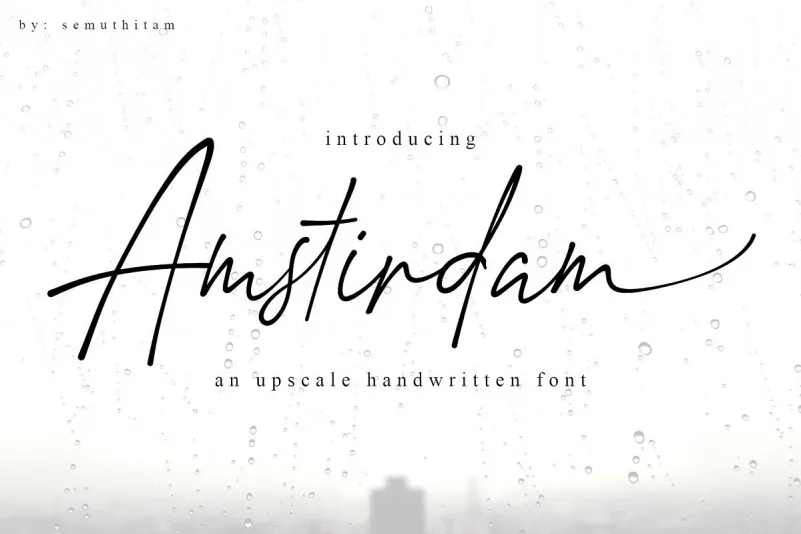
Amstirdam Handwritten Script Font – Download Grátis
Estou aqui uma descrição para a página de download da fonte ‘Amstirdam Handwritten Script Font’, adequada ao estilo e requisitos especificados: Agradecemos por verificar a fonte Amstirdam Font, um belo traço de escrita à mão! Esta tipografia contém inúmeras ligaturas divertidas que conferem ao seu design o toque único e autêntico. É uma tipografia de escrita à mão sofisticada, perfeitamente adequada para diversas finalidades: branding, convites de casamento, cartões de visita, e outros trabalhos de impressão. Esta fonte vem com um conjunto completo de letras maiúsculas e minúsculas elegantes, números, pontuação, suporte a múltiplos idiomas e uma variedade de ligações. Além disso, todas as letras minúsculas oferecem duas variações no final, garantindo-lhe um impressionante e autêntico sentido do papel da escrita à mão. Englobando o design com uma atmosfera única e envolvente, Amstirdam Handwritten Script se tornará a escolha ideal para seus projetos digitais ou impressos de alto nível.